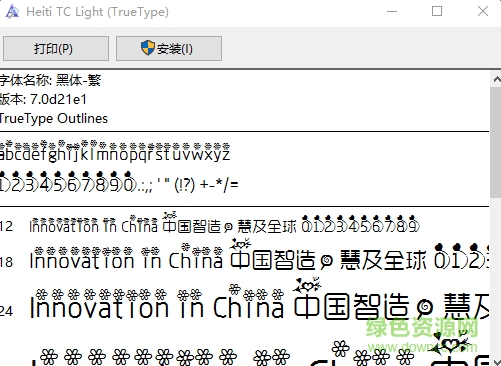
恋爱城堡字体是一款很甜蜜的电脑艺术字体,就像它的名字所说那样是一款充满了恋爱味道的字体,写出来的字也是超级好看的,用来艺术写作应该会很好看吧,欢迎大家来绿色资源网下载。
恋爱城堡字体字形非常有特色,写出来的字当然也就很有个性了,使用范围也很广,艺术设计、广告设计都是可以的,喜欢的朋友就快来绿色资源网下载吧。